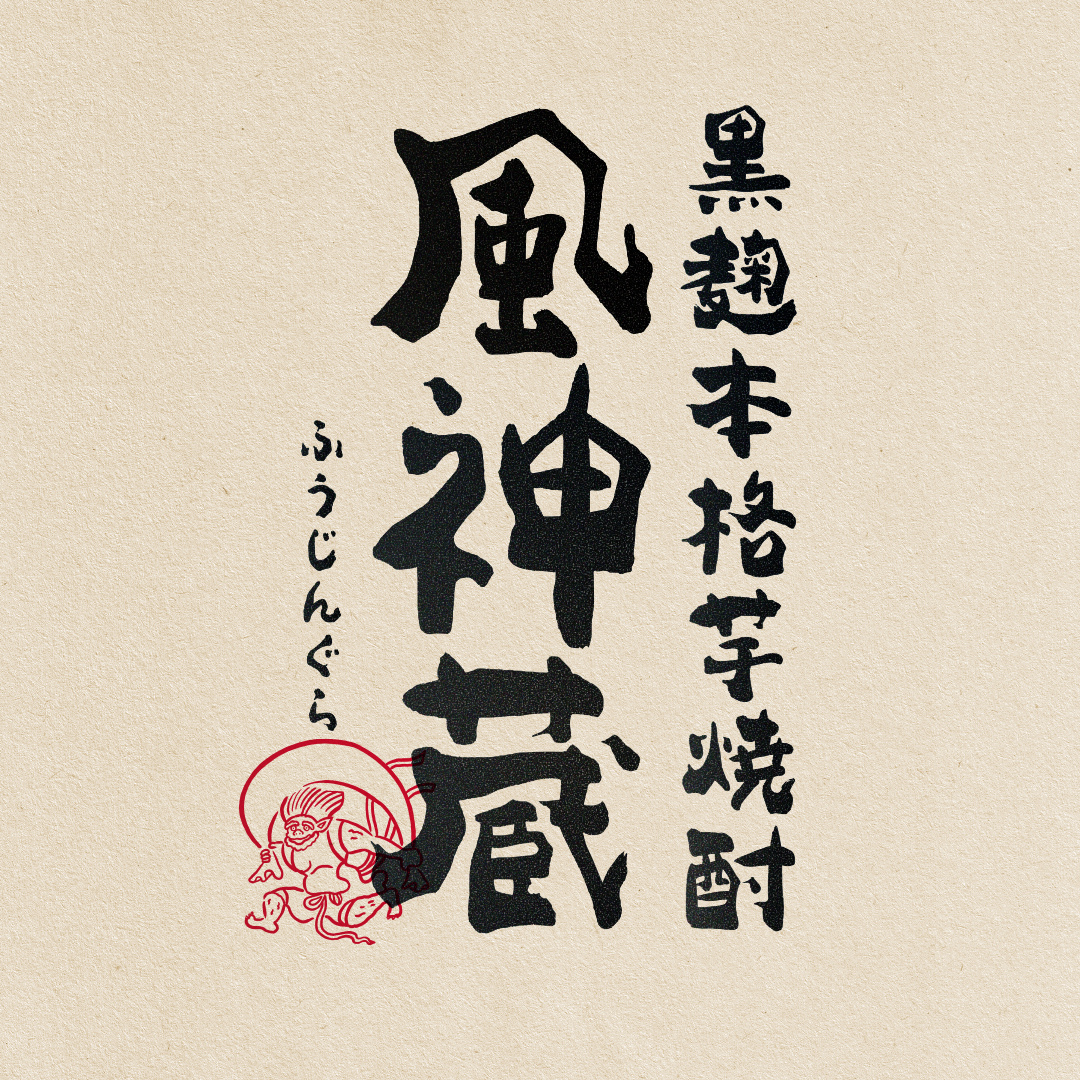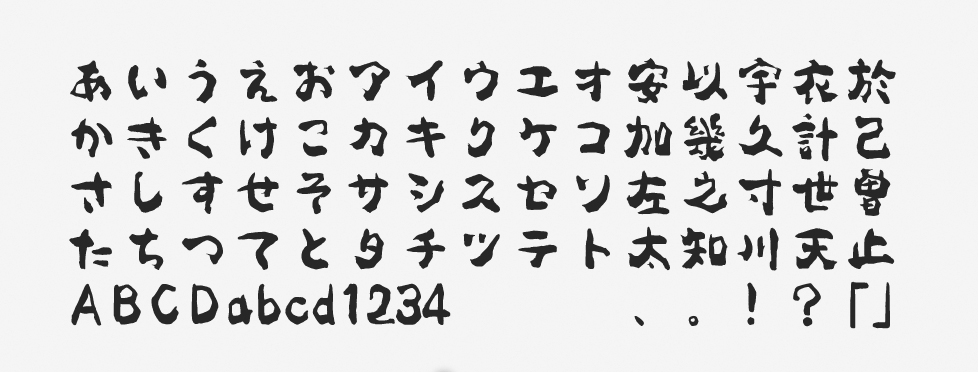
「黒曜」について
黒曜は、2017年のモリサワ新書体として登場しました。見出し用に作成されており、何よりも大胆な筆使いが特徴です。無骨で力強いイメージを表現したい場面には特に適しています。 “書” の分野のアーティスティックな雰囲気もあり、個性的でクセの強い印象を与えるフォントです。
「黒曜」の特徴
黒曜の「はね」や「はらい」には、独特な勢いがあります。まさに筆と墨で書かれたような文字で、こだわりの強さを感じさせます。題字などの大見出しをはじめ、昔話のような歴史的な表現、看板、年賀状などでも映えやすいフォントです。
線画の太い部分と細い部分の差が激しく、全体的にはたっぷりとした「黒み」がありながらもコントラストが生まれています。 “和” の雰囲気が強く、和紙と組み合わせるデザインなども効果的です。
作例では、文字を背後のイラストやテクスチャと馴染ませることで、“筆” で書いた文字”の雰囲気をさらに強調しました。書道の雰囲気、和紙の雰囲気が演出されてアナログな質感が表現できています。このような書道、筆文字系のフォントには欠かせないテクニックとして覚えておくと良いと思います。
タイトル・見出し、商品パッケージ、ロゴ、ラベル、看板、サイン、ディスプレイ広告
「黒曜」の書体情報